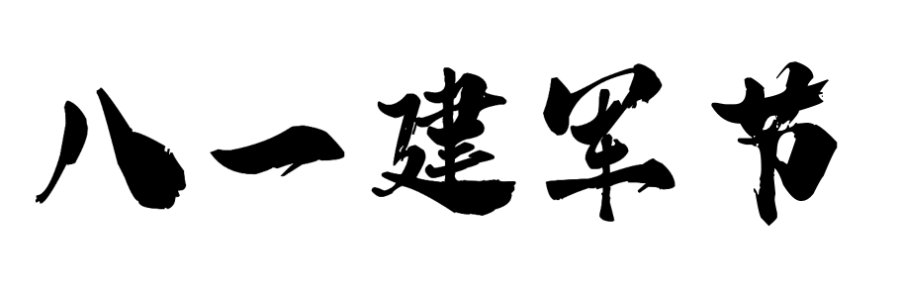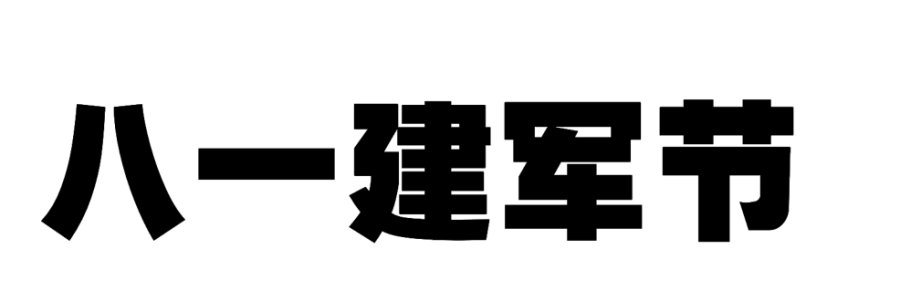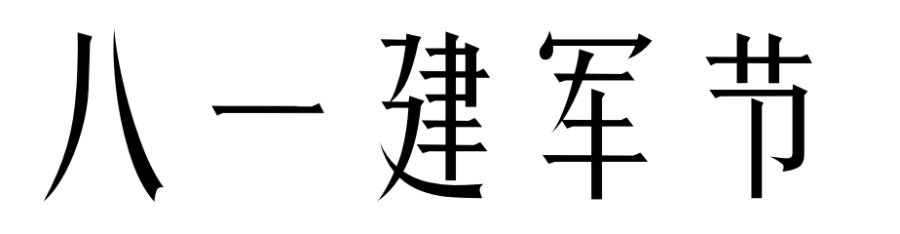
公历8月1日是建军节。1933年7月11日,中华苏维埃共和国临时中央政府决定8月1日为中国工农红军成立纪念日,也就是现在的“八一”建军节。
推荐一:汉标高清锐毛
书法味道的纯手写字体,作者运用大号毛笔精心书写,楷书味道浓厚,由于字体较大,使得笔画清晰度较高,笔画中也减少了过多的处理和笔势,厚重、饱满。因为是纯手写的原因,它独特的气质更与其他字体不同,看似统一,其实各有各的味道,每个字都可以独具风情。
推荐二:印品鸿蒙体
印品鸿蒙体结构严谨端庄,字形饱满,字体间距布局均匀讲究 ,整体美观又大方,整体风格刚劲有力而又不失俊儒之风;笔画之中蕴含古朴沉厚端凝之势,在主标题上有很大的应用空间。
推荐三:印品清秀体
印品清秀体,一款气质娟秀,清雅悦目,个性鲜明的字体,字形工整秀长,细节飘逸。笔画更加纤细修长,整体看起来舒服易读,适用于带有清和雅致风格的标题和正文排版。